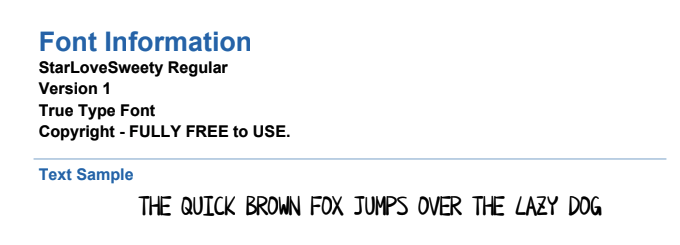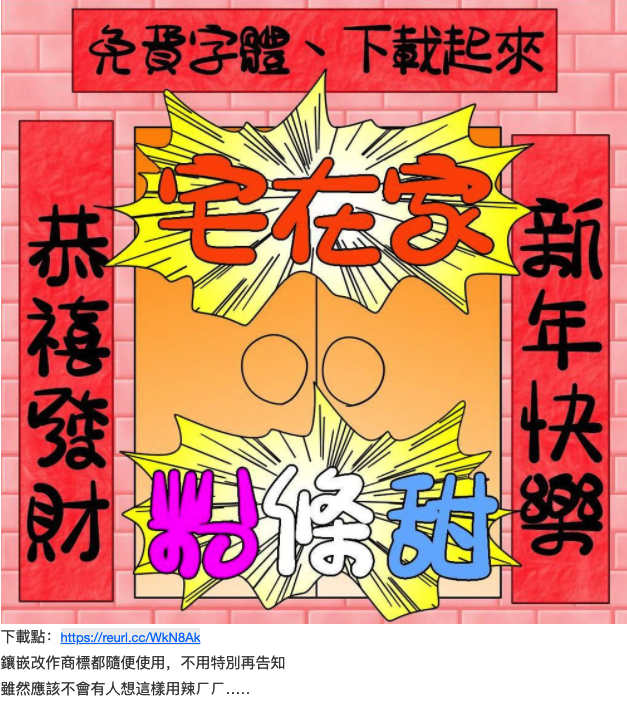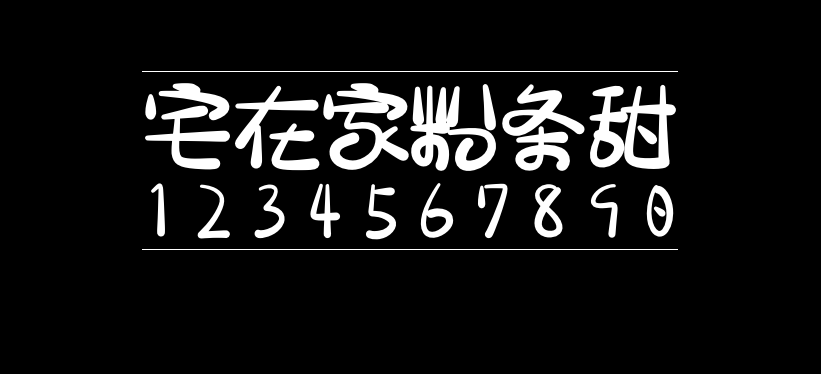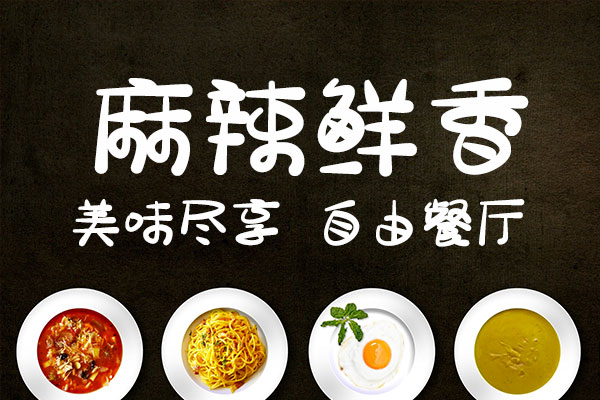
宅在家粉条甜
宅在家粉條甜(StarLoveSweety)的作者是中国台湾省的网友“天天宅在家”,在此字体发布前,作者已经发布了2款宅在家系列字体,宅在家粉条甜是作者推出的第三款免费字体。
宅在家粉条甜字体风趣可爱,圆滑Q弹,设计感十足。更难能可贵的是,作者照顾到中国大陆简体字习惯,完成了简体标准6763字,大家不用担心简体字的显示问题啦!宅在家粉条甜对简体和繁体的支持都非常好!